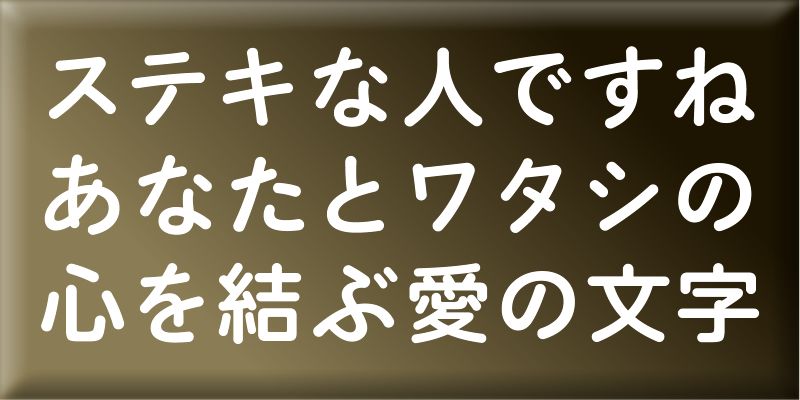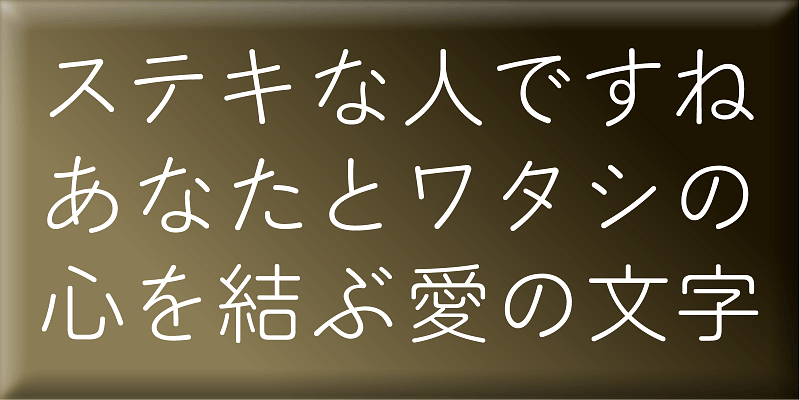
BokutohRera-5 kombiniert „Bokutohmaru”, eine abgerundete gotische Kana-Schrift mit schönen und klassischen Buchstabenformen, mit „Rera”, einer einfachen, abgerundeten gotischen Schrift. Sie verleiht dem Text ein frisches Aussehen und bleibt dennoch seriös und lesbar.